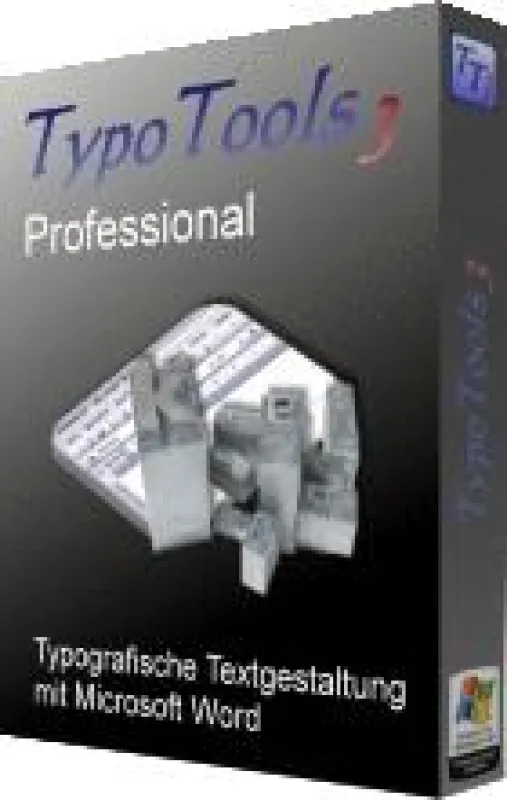
TypoTools 3: Korrekte Typografie mit Microsoft Word
TypoTools 3 Professional
(openPR) Mit Word formatierte Texte sehen gut aus, sind aber noch ein ganzes Stück vom typografischen Standard professionell gesetzter Texte entfernt. TypoTools 3 schließt die Lücke und bietet die typografischen Funktionen an, die der Textverarbeitung bislang noch fehlen.
Natürlich lassen sich in Word erfasste Texte anschließend auch gleich umfassend formatieren. Der Anwender entscheidet sich etwa für eine bestimmte Schriftart, setzt vielleicht auch noch einen Blocksatz um und sorgt mit einer guten Gliederung, hervorgehobenen Überschriften und mit abgesetzten Kopf- und Fußzeilen für ein angenehmes Layout des Textes. Allerdings: Vom Aussehen professionell gesetzter Dokumente sind die eigenen Word-Dokumente trotzdem meist noch ein ganzes Stück weit entfernt. Das ist kein Wunder. Typografisch bewanderte Experten werten ihren Text noch mit vielen zusätzlichen Formatierungen auf, die Word von Hause aus so nicht anbietet - und die das Aussehen eines Buchs, eines Berichts, einer Seminararbeit, einer Examens- oder Diplomarbeit oder einer Dissertation doch entscheidend verbessern und professioneller erscheinen lassen.
Die TypoTools 3 verpassen einem beliebigen Word-Dokument den typografischen Turbo. Zu diesem Zweck richtet die Werkzeugsammlung in Word ab der Version 2000 automatisch neue Symbolleisten ein, über die auch Anwender ohne detaillierte typografische Fachkenntnisse alle benötigten Textoptimierungen leicht aufrufen können. Das Programm ist außerdem bereits fit für Word 2007, in das es sich dank der neuen Ribbon-Technologie nahtlos integriert. Hier werden die TypoTools-Funktionen in einer eigenen Registerkarte zusammengefasst.
Was tut TypoTools 3 genau? Und was wird verändert?
Die TypoTools korrigieren zahllose kleine Layout-Fehler, die unkorrigiert dafür sorgen, dass der Text viel zu "luftig" aussieht. Ganz in diesem Sinn greift das Programm erst nach der Fertigstellung des Textes, wenn das Dokument nicht mehr inhaltlich verändert werden soll und auch der Korrekturlauf bereits erfolgt ist. Dann startet das Programm eine automatische Konvertierung, die in einem Rutsch das gesamte Dokument analysiert und alle erforderlichen Änderungen durchführt.
Dabei formatieren die TypoTools 3 Abkürzungen mit verminderten Leerzeichen, kümmern sich um einen Laufweitenausgleich und bereinigen häufige typografische Probleme wie falsche Anführungszeichen und zu kurze Bis-Striche. Möglich ist es auch, auf ein Blocksatz-Tool zur manuellen Optimierung von Laufweiten und der Silbentrennung zuzugreifen und benutzerdefinierte Ligaturen einzusetzen. Die TypoTools unterstützen auch OpenType-Schriftarten und können mit ihnen echte Kapitälchen und Mediävalziffern umsetzen. All das spart Platz und lässt den Text enger zusammenrücken.
Auf Wunsch markiert das Programm alle Änderungen farbig, sodass sie sich leicht kontrollieren lassen. Entwickler Michael Lenz: "Einzelne Funktionen von TypoTools 3 sind oft selbst in professionellen Satzprogrammen nicht enthalten. Um sie mit Word umzusetzen, müsste der Anwender manuell Hunderte von Suchen-und-Ersetzen-Kommandos durchführen."
TypoTools 3: 3 Versionen für jeden Bedarf
Die TypoTools liegen in drei Versionen vor. So kann sich jeder Anwender mit der Edition versorgen, die für seinen Zweck die richtige ist. Die TypoTools 3 Lite-Version ist ausschließlich für den privaten Bedarf vorgesehen und darf kostenfrei eingesetzt werden. Sie ändert das Dokumenten-Layout anhand typografischer Vorgaben, formatiert Abkürzungen mit verminderten Leerzeichen, fügt Ligaturen ein und bereinigt häufige typografische Probleme.